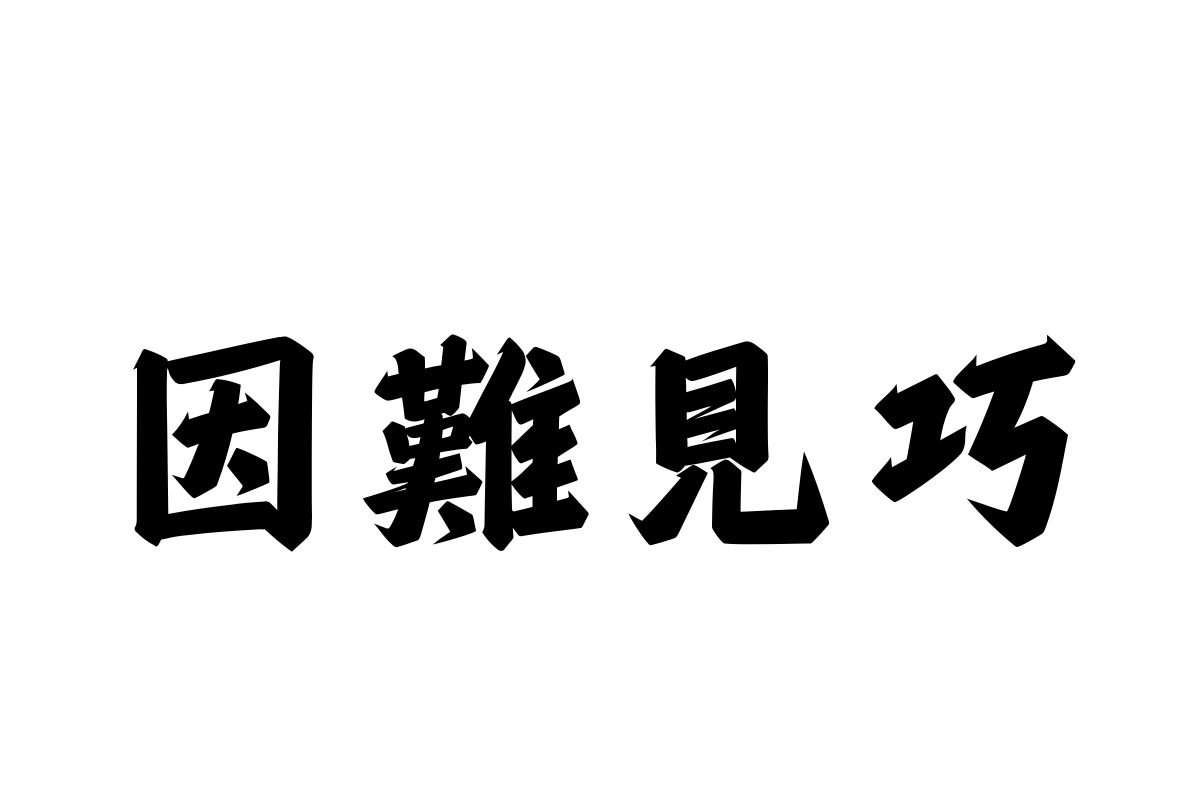
汉仪风波龙行繁体是一款具有独特设计感的字体,其笔画流畅且富有动感,给人一种强烈的视觉冲击。该字体采用了独特的风格,将传统的书法元素与现代的设计相结合,形成了一种独特的艺术效果。
这款字体的特点是笔画粗细不一,既有粗犷豪放的线条,又有细腻柔和的笔触,使得整体视觉效果更加丰富多变。同时,该字体还融入了一些现代元素,如简洁的字形结构、清晰的线条轮廓等,使得字体更具现代感和时尚感。
总的来说,汉仪风波龙行繁体是一款极具个性和创意的字体,适合用于需要强调个性和创意的设计场景,如广告设计、品牌标识、包装设计等。